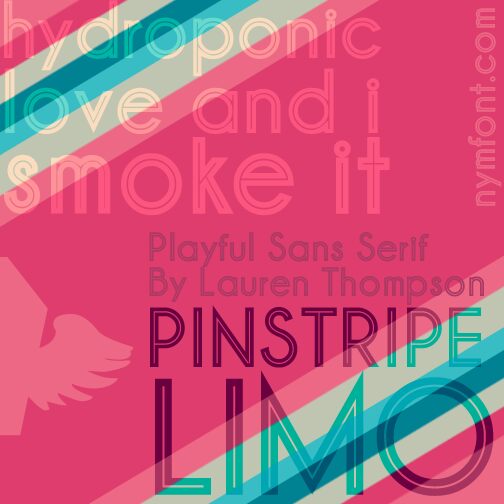
Pinstripe Limo von Lauren Thompson ist eine kostenlose Retro-Konturschrift im Display-Stil, die aus sauberen, abgerundeten Umrissen und einem schmalen inneren Streifen aufgebaut ist, der der Form jedes Buchstabens genau folgt. Die Buchstaben haben ein klares, leicht theatralisches automobiles Finish.
Klassische Autos, Nachtleben und die Unterhaltung der Jahrhundertmitte sind natürliche Themen für ihre schlanken, stromlinienförmigen Formen, wodurch sie sich gut für Eventplakate, gedruckte Musikverpackungen und beleuchtete Barschilder eignet. Bei Merchandise und Branding kann die wiederholte eingelegte Linie Teil eines größeren Nadelstreifenmusters oder eines illustrierten Abzeichens werden, anstatt nur als neutrale Beschriftung zu dienen.